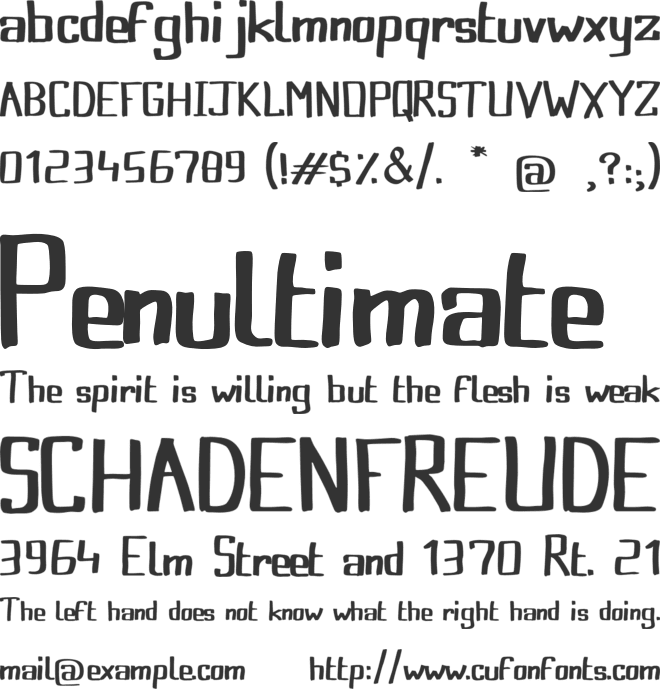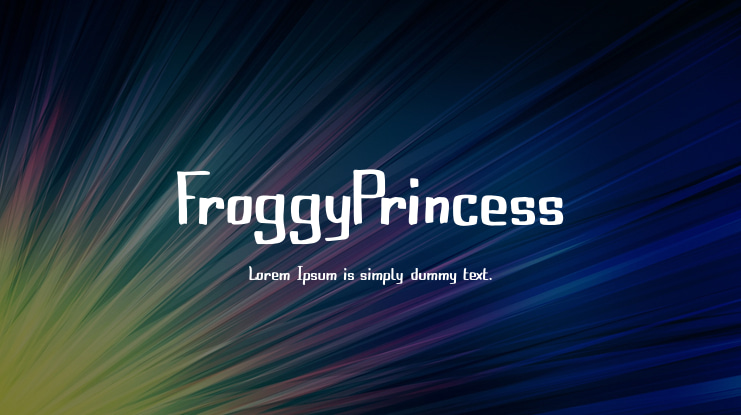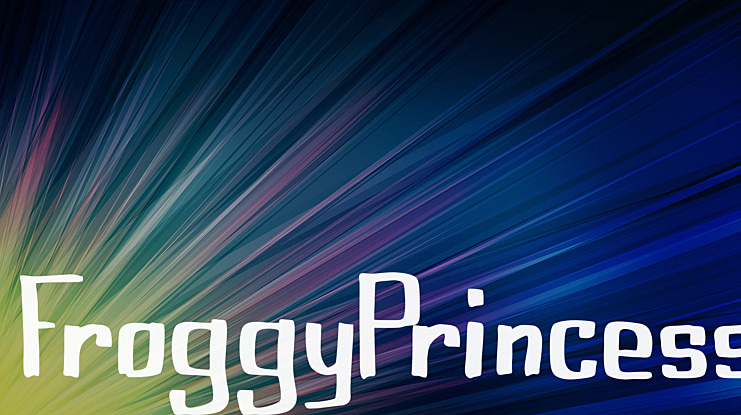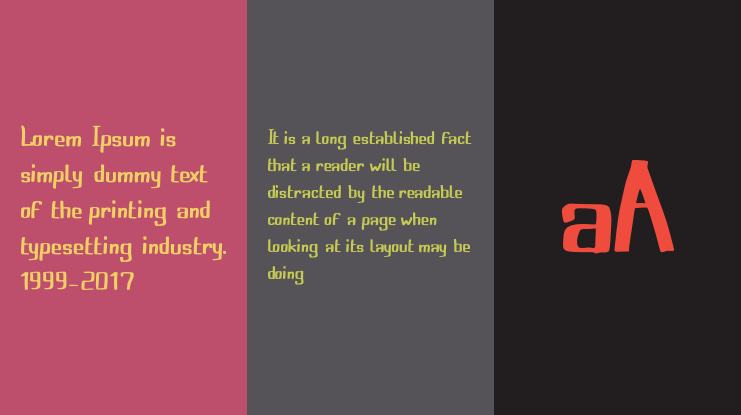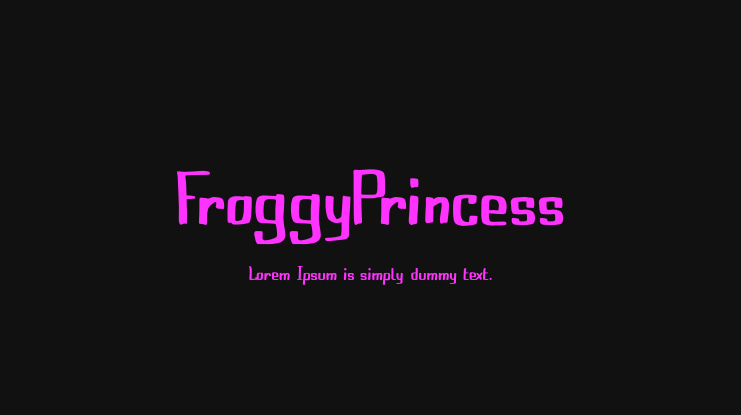
FroggyPrincess Font
Jeanne & Fabien DESPINOY
Il s'agit de réaliser une typographie girly collège, que l'on pourrait retrouver dans l’agenda d'une collégienne. Pour se faire, ma fille Jeanne, 13 ans a dessiné les lettres au surligneur fluo. Charge à moi de vectoriser les lettres de les intègrer, et de réaliser les interlettrages. Voici donc ma 4ième fonte maison.